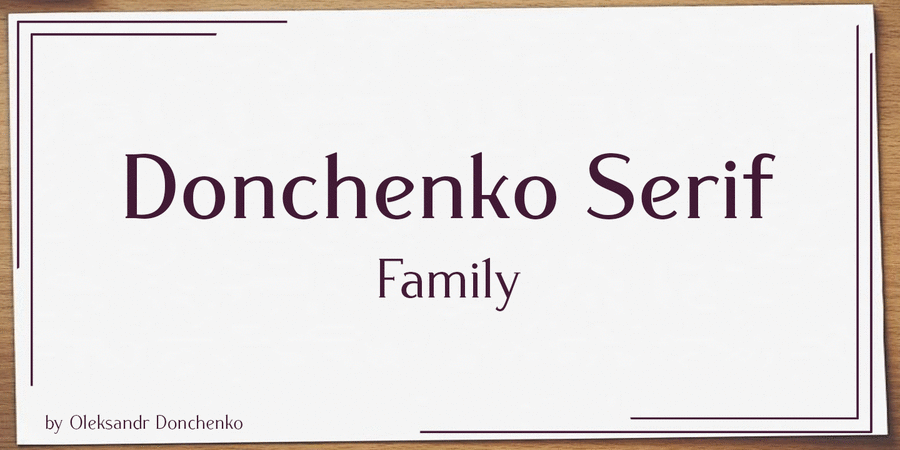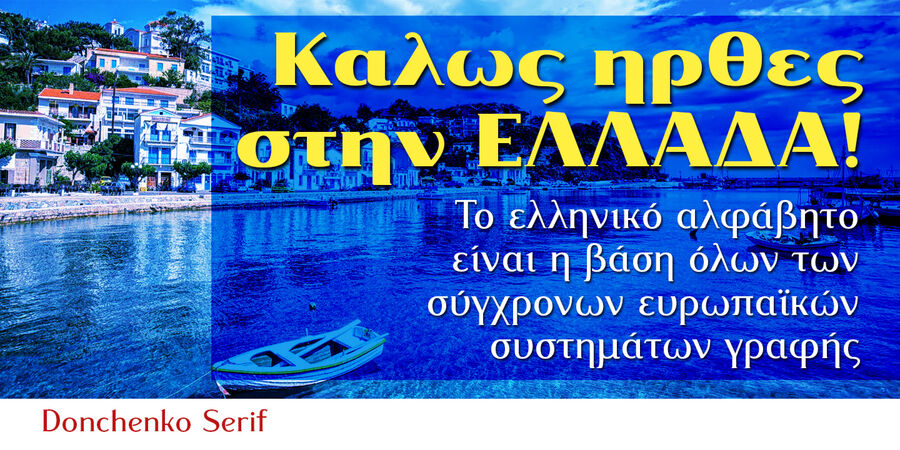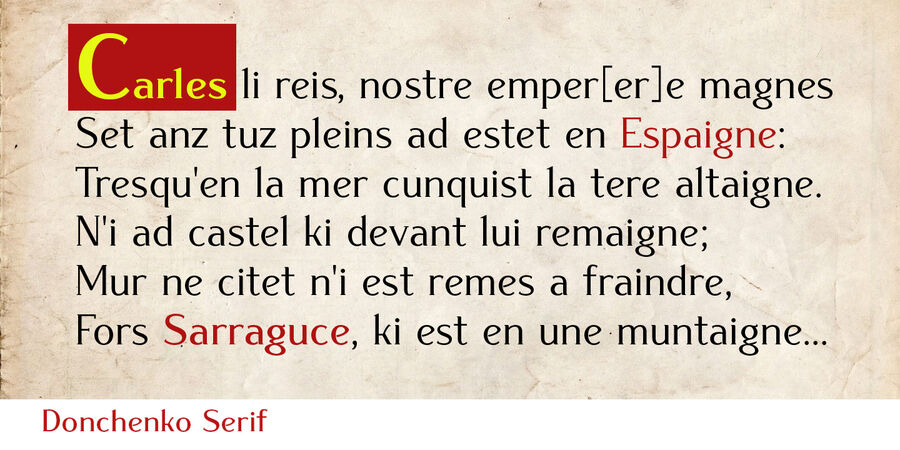
Опис гарнітури Donchenko Serif – це розмірений, елегантний шрифт із мінімалістичними засічками, який поєднує в собі відгуки до "острівних" напівунціалів із мотивами епохи модерну. Його накреслення добре читаються і водночас мають неповторні індивідуальні особливості, що дозволяє йому виділитись серед інших шрифтів цього класу.
Гарнітура Donchenko Serif – це «універсальний солдат», що чудово підготовлений для будь-яких завдань. Він добре підійде для набору текстів книжок або статей, оформлення фірмового стилю та рекламних матеріалів або створення акциденцій.
Широкий набір латинських, грецьких, кириличних і спеціальних символів забезпечує підтримку всіх європейських мов.
Шрифт Donchenko Serif був розроблений дизайнером Олександром Донченком за участю його дочки Софії Донченко у 2022 році.
Асоціації з сімейством шрифтів Donchenko SerifОсобистість і характер гарнітури:
традиційний, значний, чіткий, цінний, західний, твердий, історичний, тонкий, світлий, легкий, худий, динамічний, оригінальний, самобутній, консервативний, ностальгічний, старомодний, старовинний, антикварний, сильний, гордий, важкий, яскравий, помітний, мотивуючий, вінтажний, щедрий, сімейний, активний, різкий, рясний, насичений, дивний